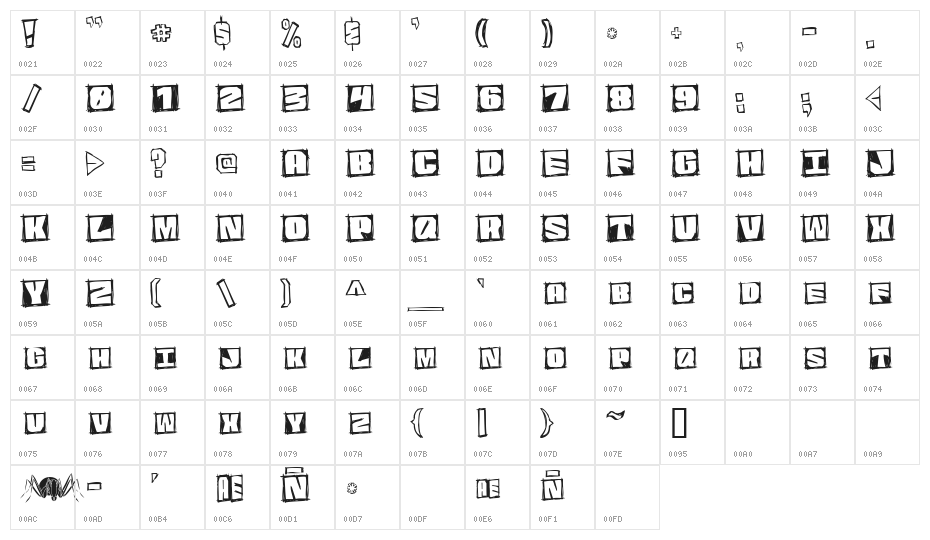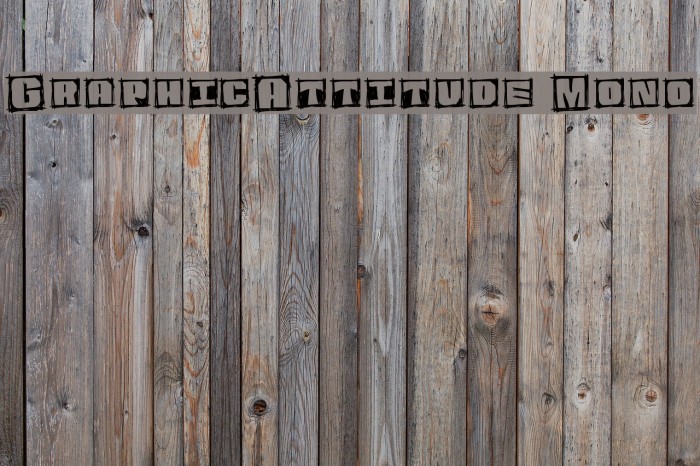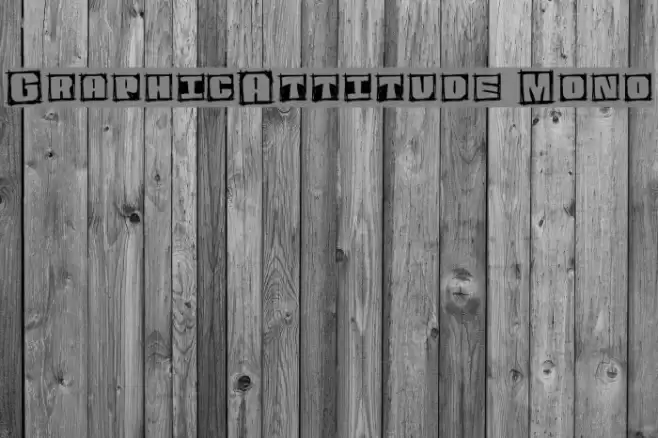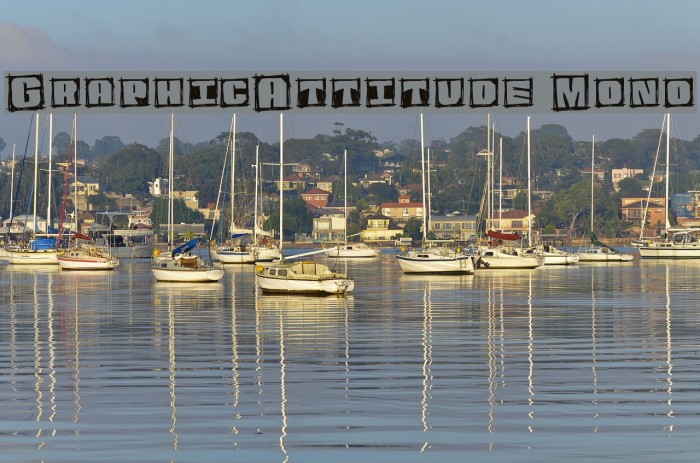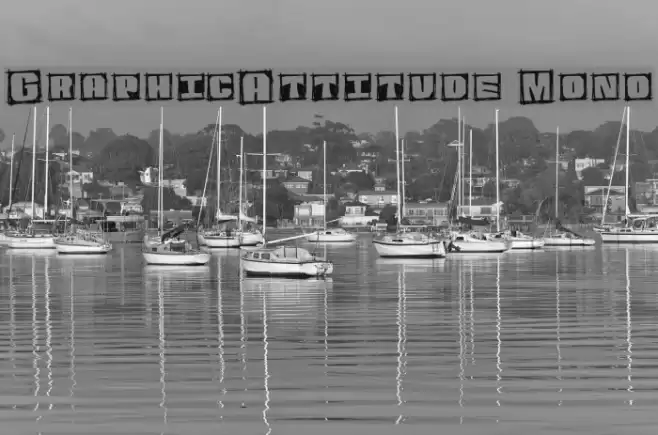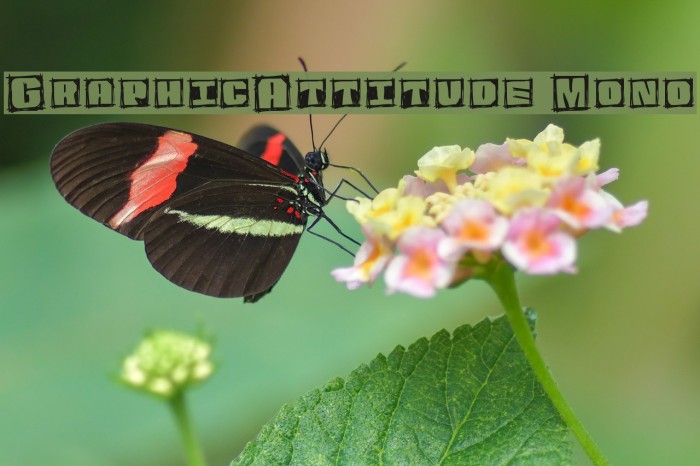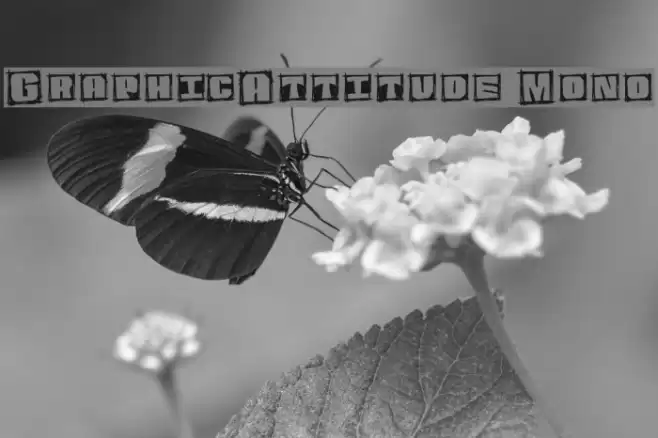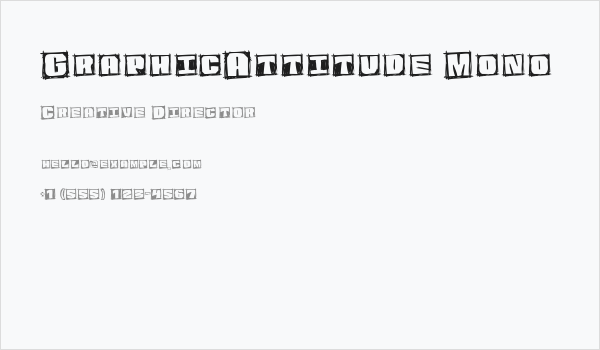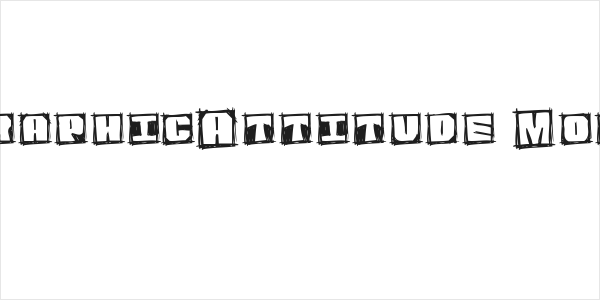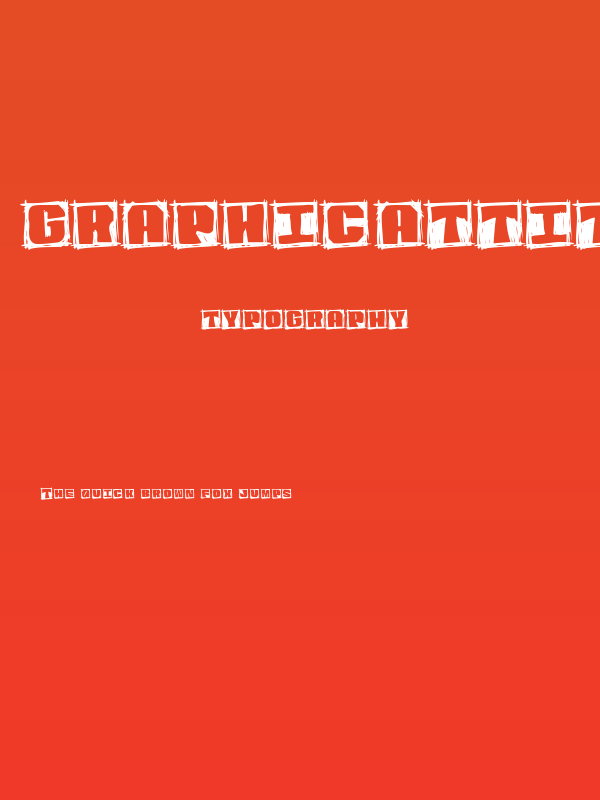
GraphicAttitude Mono Font
| おすすめプロジェクト | Ideal for urban-themed designs, music album covers, posters, and any project requiring a bold, artistic statement. |